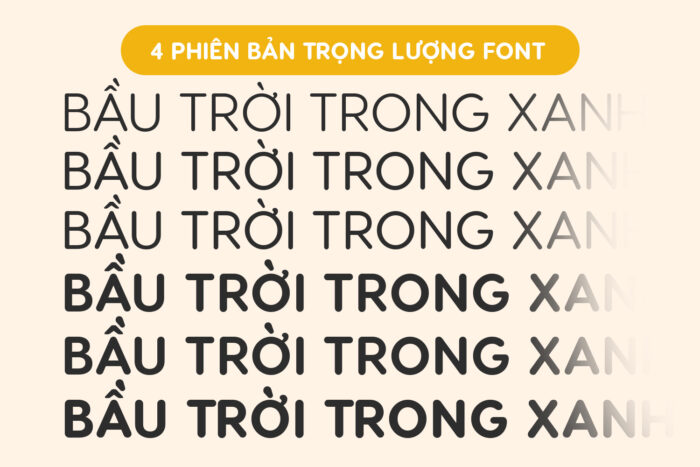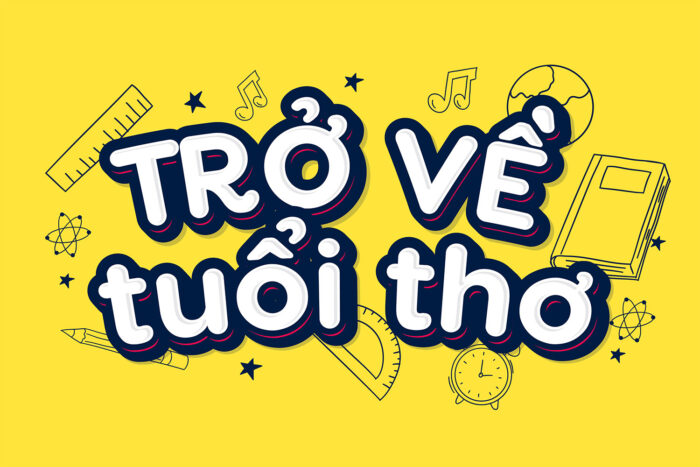
Bộ font Visby Round CF Việt hóa – Font chữ nét tròn trịa tuyệt đẹp
Bộ font Visby Round CF Việt hóa là một bộ font chữ hiện đại với các nét tròn trịa, tinh tế, phù hợp cho nhiều mục đích thiết kế từ thương hiệu, in ấn, đến web và giao diện người dùng. Với thiết kế mềm mại và trơn tru, Visby Round CF mang lại cảm giác dễ chịu, thân thiện nhưng vẫn giữ được sự chuyên nghiệp và sang trọng. Phiên bản Việt hóa của font chữ này giúp người dùng dễ dàng sử dụng trong các dự án sáng tạo yêu cầu hỗ trợ ngôn ngữ tiếng Việt đầy đủ, từ đó tạo ra các tác phẩm trực quan đẹp mắt và ấn tượng. Đặc biệt, Visby Round CF nổi bật với các ký tự bo tròn mượt mà, độ dày đồng đều, lý tưởng cho các tiêu đề, logo và cả nội dung văn bản. Đây là lựa chọn hoàn hảo cho những ai muốn thể hiện sự thanh lịch và tối giản trong thiết kế.
Phiên bản Việt hóa bao gồm 4 Style: Regular, Medium, Bold và ExtraBold